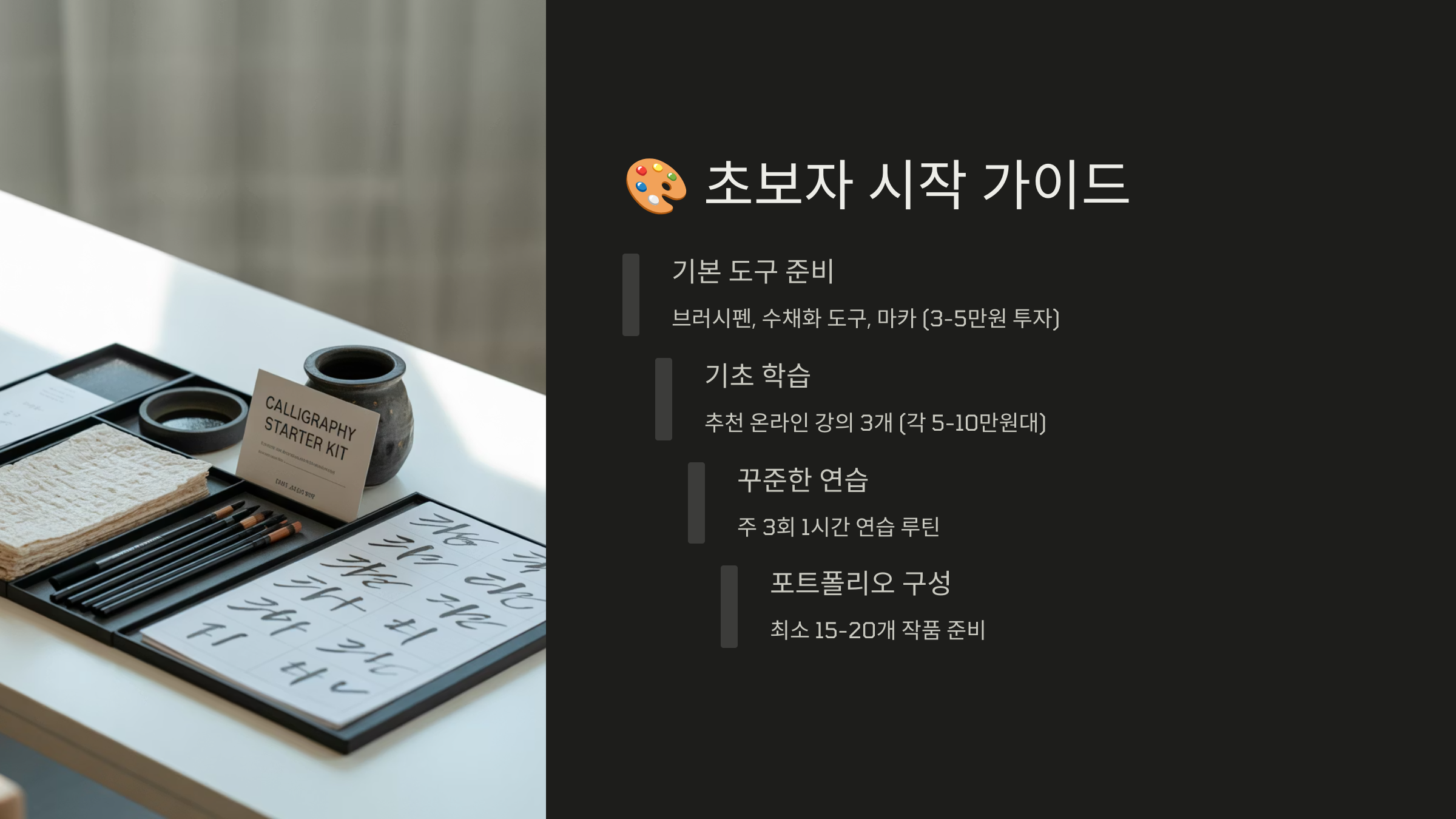
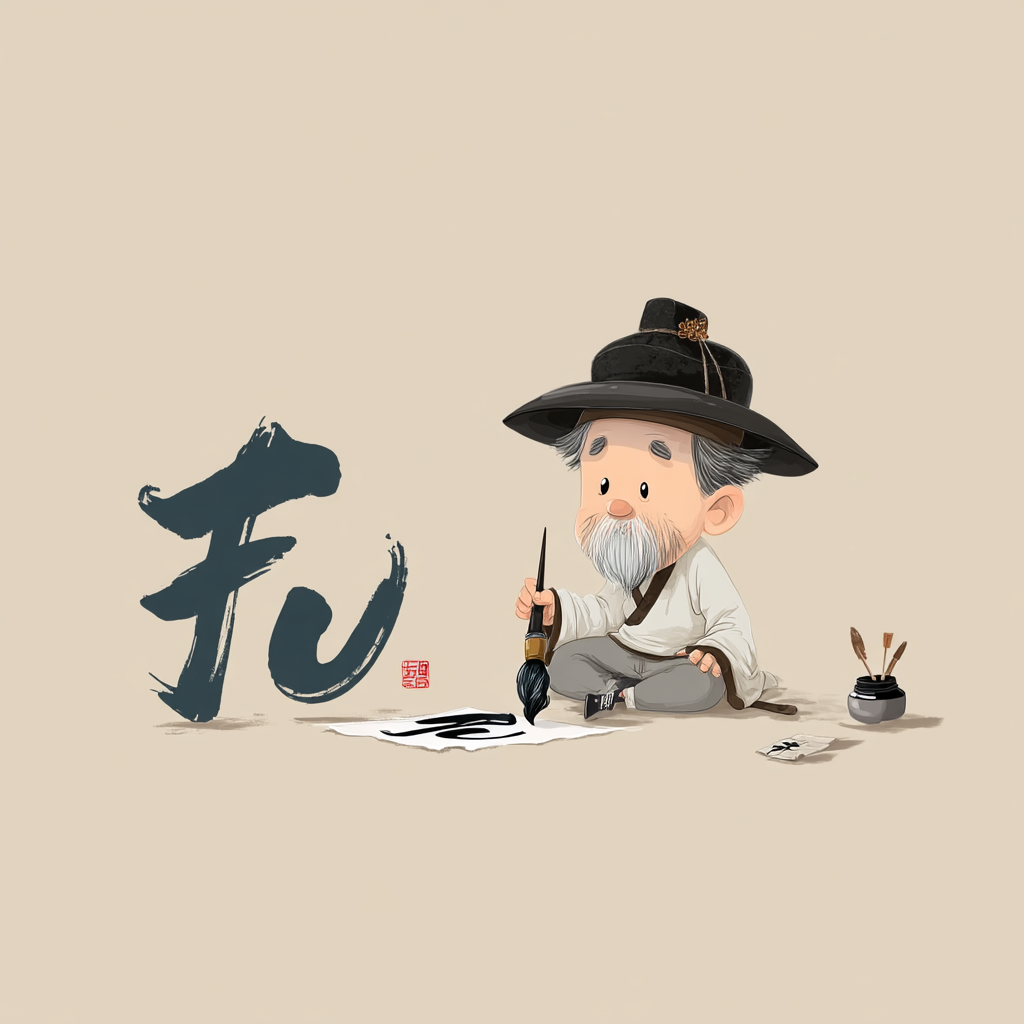
요즘 감성 있는 손글씨, 캘리그라피로 돈을 벌 수 있을까요? 많은 사람들이 취미로 시작했다가 부업, 또는 본업으로 전환하는 경우가 많아지고 있어요. 과연 이게 가능한 일인지, 진짜 수익이 나는지 궁금하셨다면 이 글에서 솔직하게 풀어드릴게요.
‘내 손글씨가 돈이 될 수 있을까?’라는 생각 한 번쯤 해보셨죠? 저도 그랬어요. 멋지게 쓴 글귀 하나에 사람들의 마음이 움직이고, 그게 상품이 된다면 너무 멋진 일이잖아요. 그래서 오늘은 캘리그라피의 세계, 수익 모델, 실제 사례까지 낱낱이 공개해볼게요! 🎨
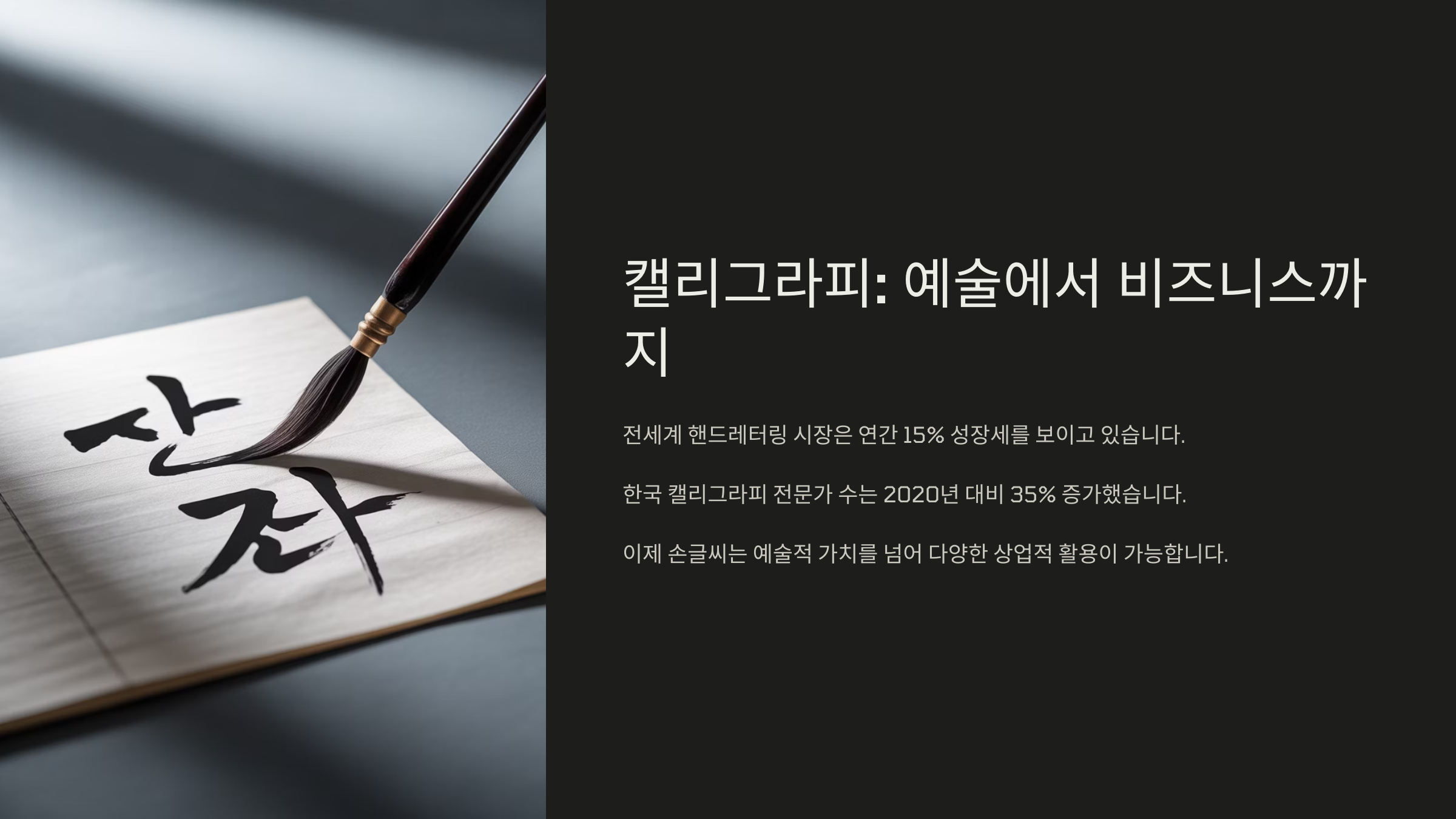
지금부터 캘리그라피로 돈 버는 현실 이야기, 시작할게요! 아래는 전체 글의 일부이며, 곧 다음 섹션에서 계속 이어질 거예요.
✍ 캘리그라피란 무엇인가요?
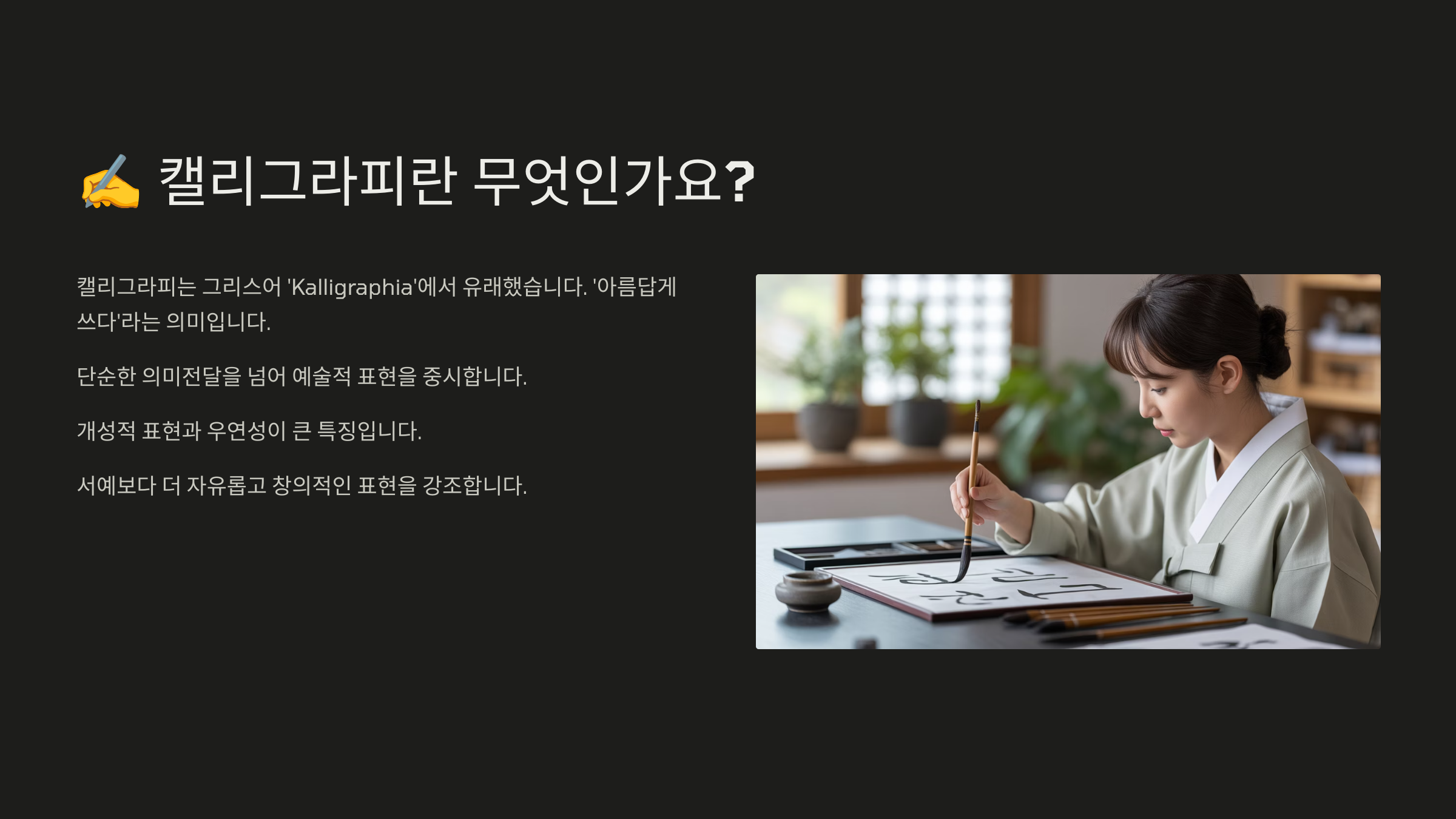
캘리그라피란 무엇인가요
캘리그라피(Calligraphy)는 아름답게 글씨를 쓰는 예술이에요. 단순한 손글씨가 아니라, 표현력과 창의력을 담아 감성을 전달하는 방식이죠. 요즘에는 디지털 캘리그라피도 많지만, 손으로 직접 그리는 전통 방식도 여전히 많은 사랑을 받고 있어요.특히 한국에서는 한글 캘리그라피가 독창적인 형태로 발전하고 있어요. 붓펜, 만년필, 마커 등 다양한 도구를 활용해 각자의 스타일을 표현하죠. 글자가 그림처럼 다가오는 매력이 있어요.
과거에는 책 표지나 간판에서 많이 활용되었지만, 요즘은 결혼식 청첩장, 유튜브 썸네일, 굿즈 디자인, 인스타그램 콘텐츠 등 활용 범위가 엄청 넓어졌어요. 덕분에 수요도 늘고 있고요.
디자인 툴 없이도 감성 하나로 승부할 수 있는 분야라는 점에서, 창작자들에게 인기가 많아요. 나만의 감성을 담을 수 있다는 건 정말 매력적인 일이죠.
🖌 캘리그라피 도구 비교표
도구 장점 단점 적합 용도 붓펜 붓 느낌 그대로 표현 가능 잉크 조절이 어려움 전통 캘리그라피 마커펜 초보자도 쉽게 사용 디테일한 표현 어려움 연습용, 감성문구 만년필 고급스러운 느낌 가격이 다소 비쌈 감성 글귀 제작 디지털 펜 편집 가능, 수정 용이 장비 필요 SNS 콘텐츠, 상업용 내가 생각했을 때 캘리그라피는 손맛이 생명이라고 느껴요. 도구에 따라 느낌이 확 달라지고, 글자 하나에 감정이 스며드는 게 신기할 정도예요. 이게 바로 캘리그라피만의 매력 아닐까요?
캘리그라피는 단순한 취미를 넘어서, 예술적인 표현 수단으로 발전하고 있어요. 특히 요즘처럼 개성과 감성이 중요한 시대에는 캘리그라피의 가치가 더 주목받고 있답니다.
글씨를 쓰는 일은 오래된 전통이지만, 그 속에서 새로운 시장이 탄생하고 있어요. 나만의 손글씨로 감동을 전하고, 수익까지 연결되는 일이라니 정말 멋지지 않나요? 💕
지금부터는 이 감성적인 캘리그라피가 실제로 돈이 되는 구조를 알아볼 차례예요. 다음 박스에서는 시장 트렌드부터 자세히 들려드릴게요!
👇 다음은 "💼 캘리그라피 시장 규모와 흐름"으로 계속 이어져요!
💼 캘리그라피 시장 규모와 흐름
캘리그라피 시장 규모와 흐름 캘리그라피는 단순한 예술을 넘어 다양한 산업과 결합되며 하나의 시장으로 성장하고 있어요. 특히 감성 마케팅이 중요해진 요즘, 손글씨의 진정성과 개성은 브랜드와 고객을 연결하는 힘이 되죠.
실제로 국내 디자인 콘텐츠 시장에서 캘리그라피는 꾸준한 수요를 보이고 있어요. 문화체육관광부 자료에 따르면, 감성 콘텐츠 수요가 최근 5년간 연평균 7%씩 성장하고 있다고 해요. 여기서 캘리그라피가 차지하는 비중도 점점 늘고 있어요.
브랜딩 작업, 상품 패키징, 광고 문구, 감성 굿즈 등에서 캘리그라피를 활용하는 기업이 많아졌어요. 특히 중소상공인이나 1인 브랜드에서 감성 요소를 넣기 위해 캘리그라피를 적극적으로 도입하고 있죠.
SNS 플랫폼의 확산도 시장 성장에 크게 기여했어요. 인스타그램, 블로그, 유튜브 썸네일 등 감성을 중시하는 콘텐츠에는 손글씨가 눈에 띄게 활용되고 있어요. 이건 단순한 예쁘기 이상의 브랜딩 전략이기도 해요.
📊 캘리그라피 활용 분야 요약표
분야 활용 예시 수요 수준 광고/홍보 간판, 포스터, 전단지 높음 제품 디자인 패키징, 라벨 중간~높음 문화예술 전시, 캘리 작품 판매 중간 SNS콘텐츠 썸네일, 배경 이미지 매우 높음 이벤트용 청첩장, 돌잔치 초대장 중간 이렇듯 다양한 분야에서 캘리그라피가 활용되고 있어요. 감성과 개성을 중시하는 트렌드 속에서 이 시장은 앞으로도 꾸준히 성장할 가능성이 커요. 특히 온라인에서 자신만의 글씨체를 콘텐츠화 할 수 있다는 점이 강점이죠.
시장 흐름을 보면 캘리그라피는 단지 예쁜 글씨가 아니라, 고객과 소통하는 새로운 언어예요. 브랜드 메시지를 감성적으로 전달하거나, 상품에 감동을 더할 수 있어요.
특히 MZ세대는 '느낌 있는 콘텐츠'를 선호하는데, 이들과 소통하려는 브랜드라면 캘리그라피는 훌륭한 선택이 될 수 있어요. 이 감성 마케팅의 흐름은 꽤 오래 지속될 전망이에요.
다음은 진짜 중요한 이야기! 캘리그라피로 실제 수익을 만드는 방법 5가지를 자세히 알아볼게요. 실제로 돈이 되는 구조가 궁금하다면 꼭 봐야 할 내용이니 놓치지 마세요. 💰
💰 캘리그라피 수익모델 5가지
캘리그라피 수익모델 5가지
그럼 진짜 중요한 이야기로 들어가 볼게요! 캘리그라피로 돈을 벌 수 있는 현실적인 방법은 생각보다 다양해요. 단순히 작품 판매뿐 아니라 디지털과 결합한 수익 구조도 가능하답니다.첫 번째는 '굿즈 제작 및 판매'예요. 엽서, 머그컵, 다이어리, 스티커, 탁상달력 등 감성을 담은 캘리그라피 문구는 구매욕을 자극해요. 요즘엔 스마트스토어나 마켓플레이스를 통해 쉽게 판매할 수 있어서 진입장벽도 낮아요.
두 번째는 '디자인 의뢰 작업'이에요. 기업 로고, 제품 패키지, SNS 콘텐츠용 캘리, 유튜브 썸네일 작업 등이 이에 해당해요. 포트폴리오만 잘 구성해두면 작업 요청이 꾸준히 들어오고, 단가는 적지 않은 편이에요.
세 번째는 '온라인 클래스 개설'이에요. 클래스101, 탈잉, 크몽 등 플랫폼에서 수업을 열면 수익을 창출할 수 있어요. 초보자 대상 기본 강좌부터 심화 과정까지 커리큘럼을 구성할 수 있고, 수강생 피드백으로 인지도도 올라가요.
💡 캘리그라피 수익 모델 요약표
수익 모델 설명 수익 예측 굿즈 판매 캘리로 제작한 상품 판매 월 30만~100만 원 디자인 의뢰 클라이언트 작업 건당 5만~30만 원 온라인 강의 클래스 개설 및 수강생 확보 1강좌당 최대 200만 원 이상 디지털 캘리 판매 PNG, AI 파일로 상업용 등록 건당 1천 원~5만 원 현장 이벤트 캘리그라피 부스 운영 1회당 10만~50만 원 네 번째는 '디지털 캘리 판매'예요. 텍스트나 이미지 파일을 PNG, SVG, AI 등으로 만들어 마켓에 등록하면 필요로 하는 사람들이 구매해요. 특히 티셔츠, 포스터 디자인에 자주 활용돼요.
다섯 번째는 '행사 부스 참여'예요. 플리마켓이나 기업행사, 북페어 같은 곳에서 직접 써주는 라이브 캘리그라피 서비스가 인기가 많아요. 단가도 높고 현장에서 바로 수익을 낼 수 있다는 장점이 있죠.
이처럼 수익 모델은 창의력과 결합해 다양한 방식으로 확장할 수 있어요. 혼자서도 시작할 수 있고, SNS를 기반으로 인지도까지 올릴 수 있어서 자기만의 브랜드를 키우기 좋은 분야예요.
다음 박스에서는 실제 캘리그라피 수익을 낸 분들의 생생한 후기를 공개할게요! 현실적인 사례를 보면 동기부여도 되고 방향도 잡히니까 꼭 확인해 주세요. 📈
📈 실제 수익 후기 및 사례
실제 수익 후기 및 사례
이번에는 실제로 캘리그라피로 수익을 올린 분들의 생생한 후기를 소개할게요. "진짜 돈이 될까?"라는 질문에 가장 현실적인 답을 줄 수 있는 건 바로 경험자들의 이야기니까요.1. 첫 번째 사례는 직장인이었던 김지은 님이에요. 야근 많은 회사를 다니다 우연히 시작한 붓펜 캘리그라피가 계기가 되어, 퇴근 후 인스타에 글귀를 꾸준히 올렸고, 1년 뒤엔 온라인 클래스까지 개설했어요. 월 200만 원의 부수입이 생기자 아예 프리랜서로 전향했다고 해요!
2. 두 번째는 육아맘 이윤아 님. 출산 후 경력 단절이 고민이었는데, 아이가 자는 시간 틈틈이 굿즈를 만들기 시작했대요. 청첩장 글귀, 가랜드 문구, 소품샵 협업으로 월 평균 50만~100만 원까지 수익을 올리고 있답니다. 시간 제약 많은 사람에게 딱이에요!
3. 세 번째는 대학생 박선우 님. 전공은 디자인과 무관했지만 감성 글귀에 푹 빠져 매일 하나씩 연습하며 SNS에 기록했어요. 그러던 중 한 서점에서 라이브 캘리 부스를 열게 되었고, 해당 경험이 포트폴리오가 되어 기업 브랜딩 디자인까지 맡게 됐다고 해요.
🧾 캘리 수익 사례 비교표
이름 출발점 수익 방식 월 수익 김지은 퇴근 후 취미 온라인 클래스, 디자인 200만 원 이윤아 육아 틈틈이 굿즈 제작, 초대장 문구 100만 원 박선우 대학생 연습생 부스 운영, 브랜드 디자인 150만 원 이처럼 캘리그라피는 연령대, 상황, 출발점이 달라도 충분히 수익 모델을 만들 수 있는 분야예요. 중요한 건 자신만의 감성과 꾸준함, 그리고 온라인을 잘 활용하는 센스예요.
수익을 만들기 위해 꼭 전문가 수준의 실력이 필요한 건 아니에요. 오히려 사람들은 '따뜻하고 진심이 느껴지는' 손글씨를 더 좋아해요. 연습하면서 나만의 스타일을 만들어가는 게 핵심이에요.
또한, 수익 창출에는 플랫폼 선택도 중요해요. 크몽, 탈잉, 스마트스토어, 인스타그램, 클래스101 등 다양한 채널을 자신에 맞게 활용해 보세요. 플랫폼마다 잘 맞는 콘텐츠 스타일이 있어요.
이제부터는 어떻게 수익을 더 키울 수 있는지 실전 노하우를 알려드릴게요! 감성만 믿고 도전하는 것도 좋지만, 전략도 함께 챙겨야 더 멀리 갈 수 있으니까요 🚀
🚀 수익을 위한 실전 팁
수익을 위한 실전 팁 실제로 수익을 만드는 분들은 단순히 감성만으로 승부하지 않아요. 전략과 방향성도 함께 잡고 있죠. 여기서부터는 수익화에 바로 활용할 수 있는 실전 팁들을 알려드릴게요!
Q3. 캘리그라피 의뢰는 어디서 받나요?
A3. 크몽, 탈잉, 인스타그램 DM, 블로그 포스팅 등에서 클라이언트가 직접 연락하는 경우가 많아요. 포트폴리오 노출이 중요해요.
Q4. 어떤 도구로 시작하는 게 좋을까요?
A4. 초보자에게는 모나미 붓펜이나 트윈펜이 좋아요. 가격도 저렴하고 연습용으로 딱이에요.
Q5. 글씨에 자신이 없는데 해도 될까요?
A5. 글씨체보다 중요한 건 감성과 표현력이에요. 잘 쓴 글씨보다 '느낌 있는' 글씨가 더 사랑받는 시대예요.
Q6. 온라인 클래스는 어떻게 시작하나요?
A6. 클래스101, 탈잉 등에서 강사 신청서를 작성하면 심사를 통해 개설할 수 있어요. 커리큘럼과 샘플 영상이 중요해요.
Q7. 캘리그라피 콘텐츠 저작권은 어떻게 되나요?
A7. 자신이 직접 쓴 작품은 당연히 저작권이 있어요. 단, 타인의 글귀나 명언을 사용할 땐 출처를 밝혀야 해요.
Q8. 캘리그라피로 사업자 등록도 가능한가요?
A8. 네, 가능합니다! 디자인, 예술, 교육 분야로 등록할 수 있고, 온라인 판매나 강의가 있다면 사업자 등록이 유리해요.